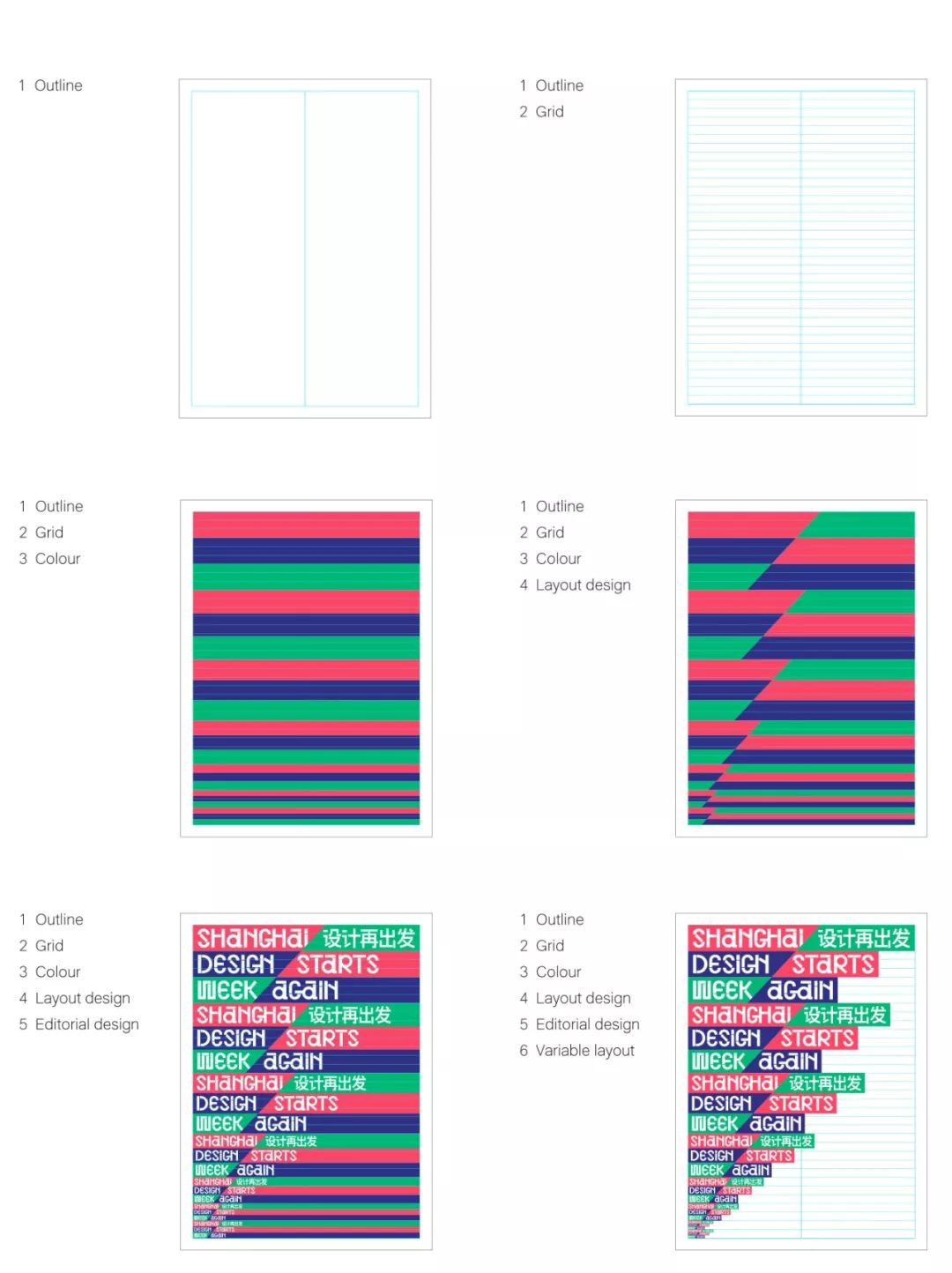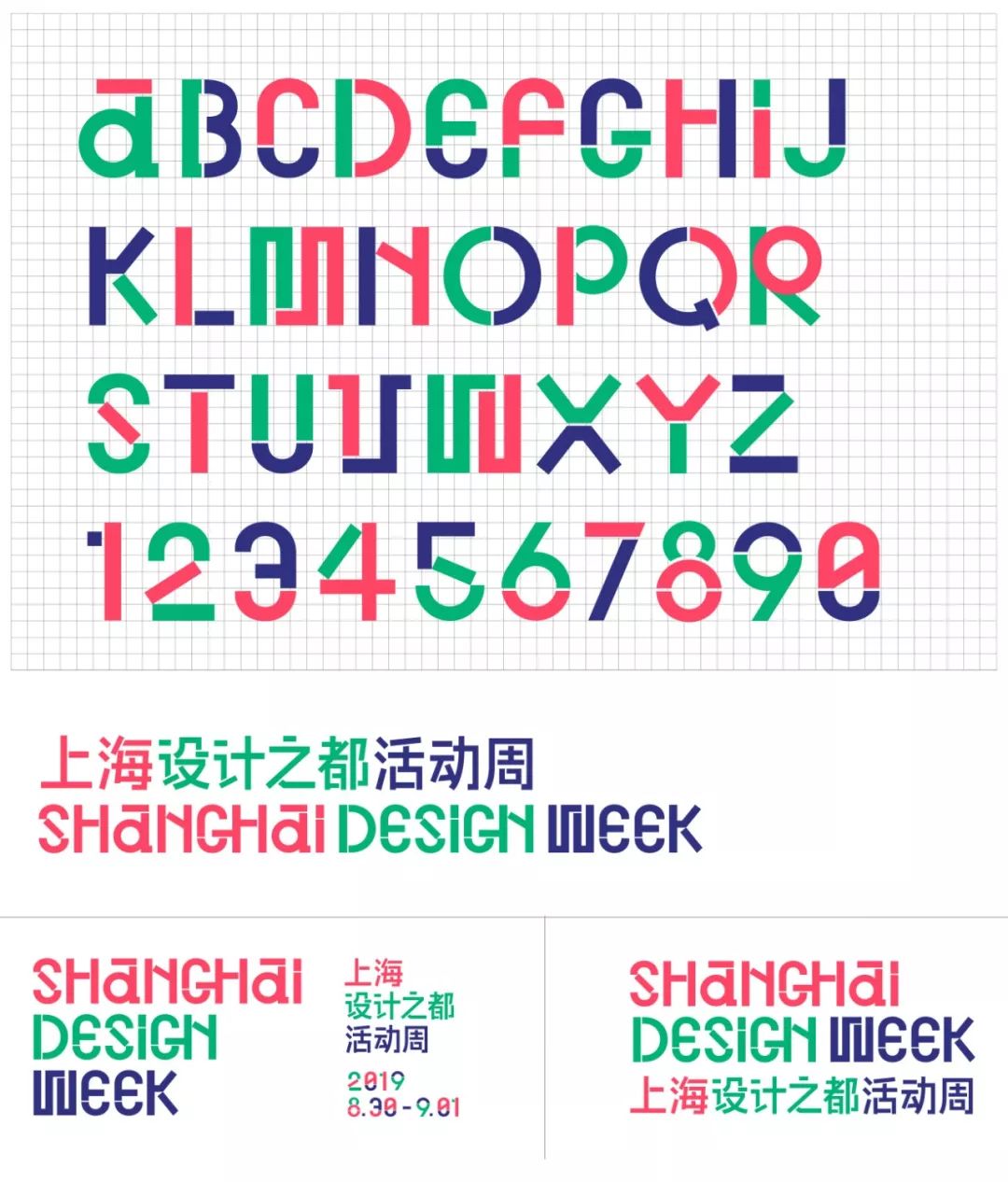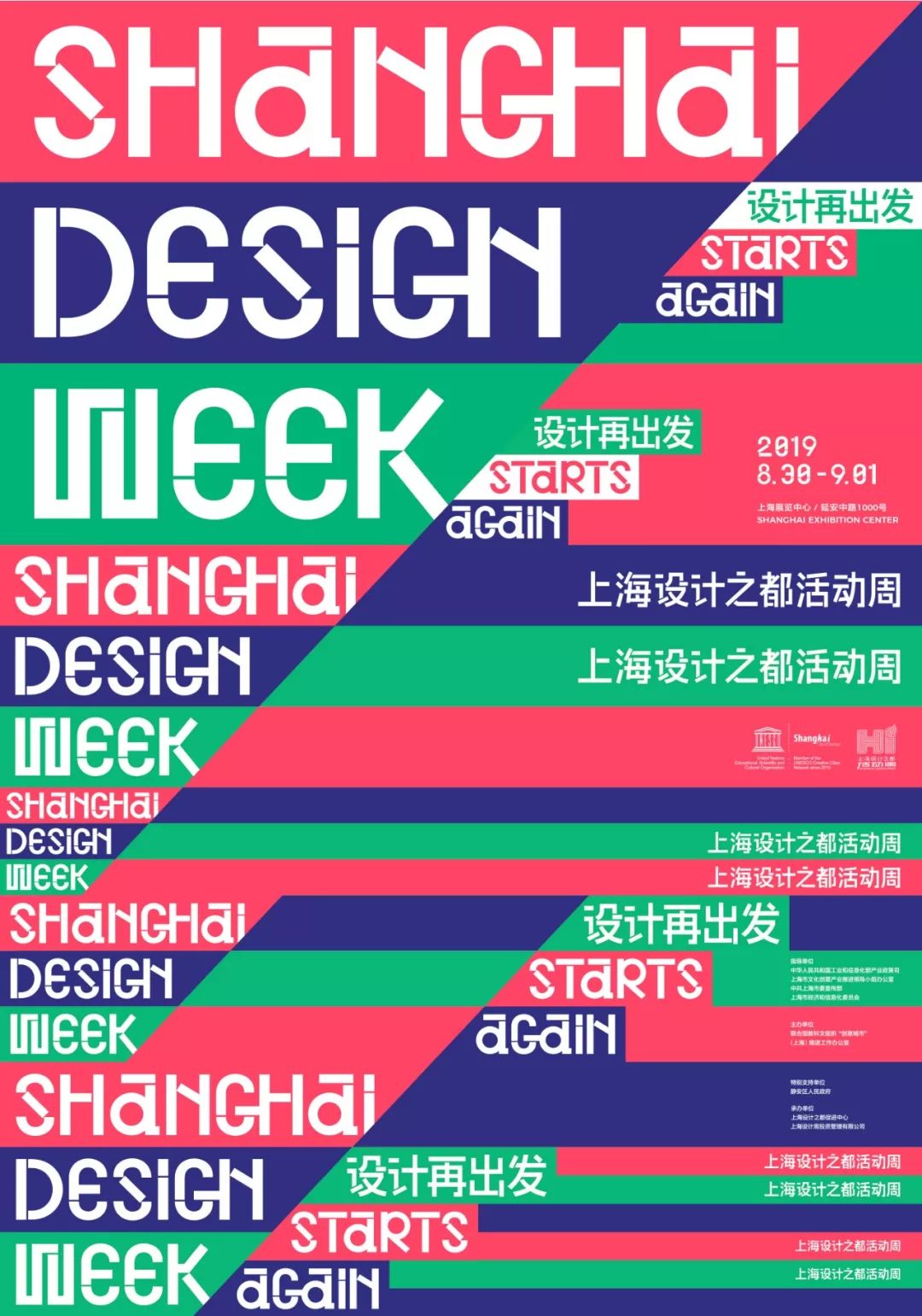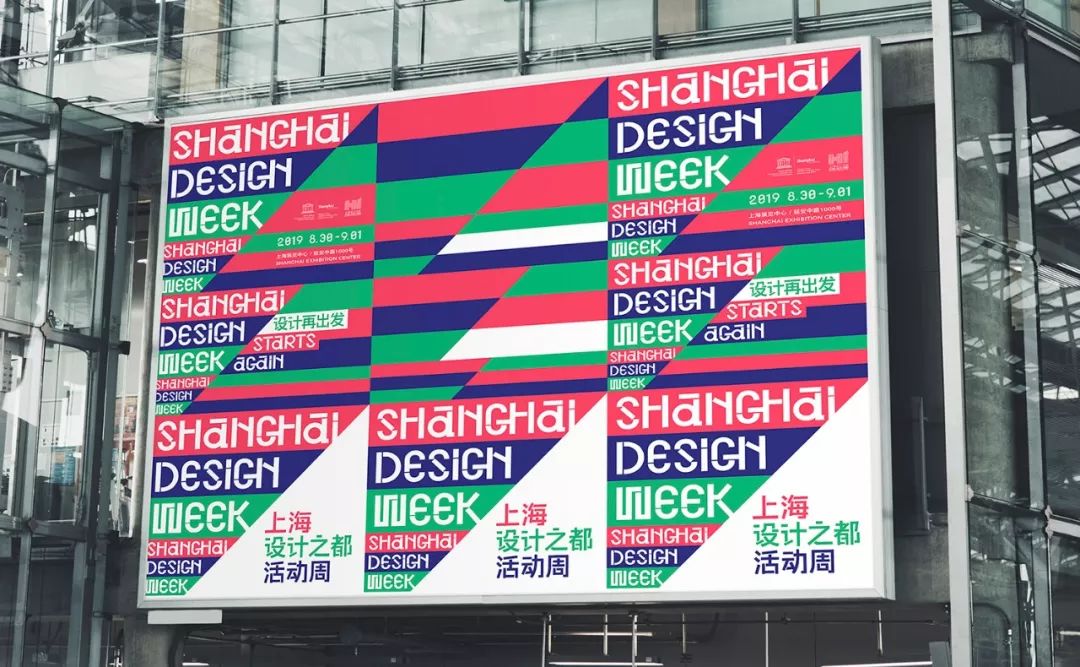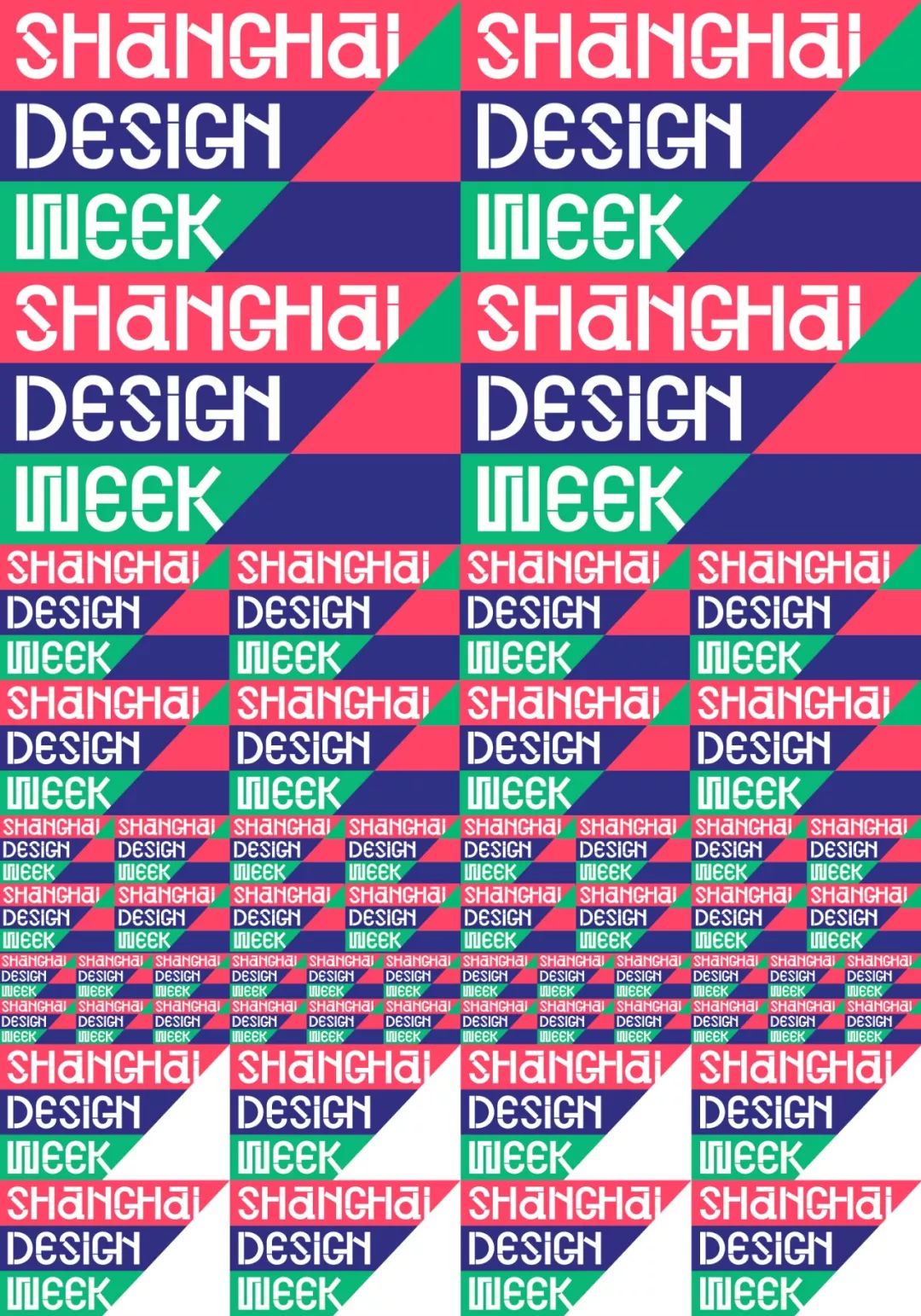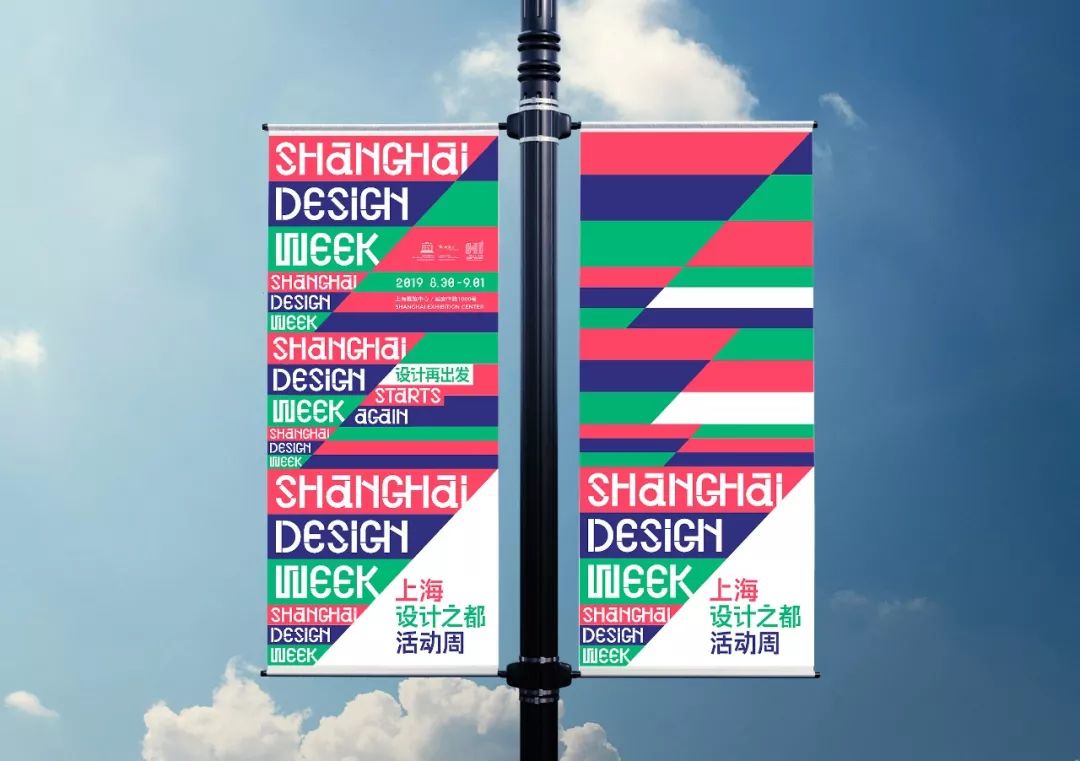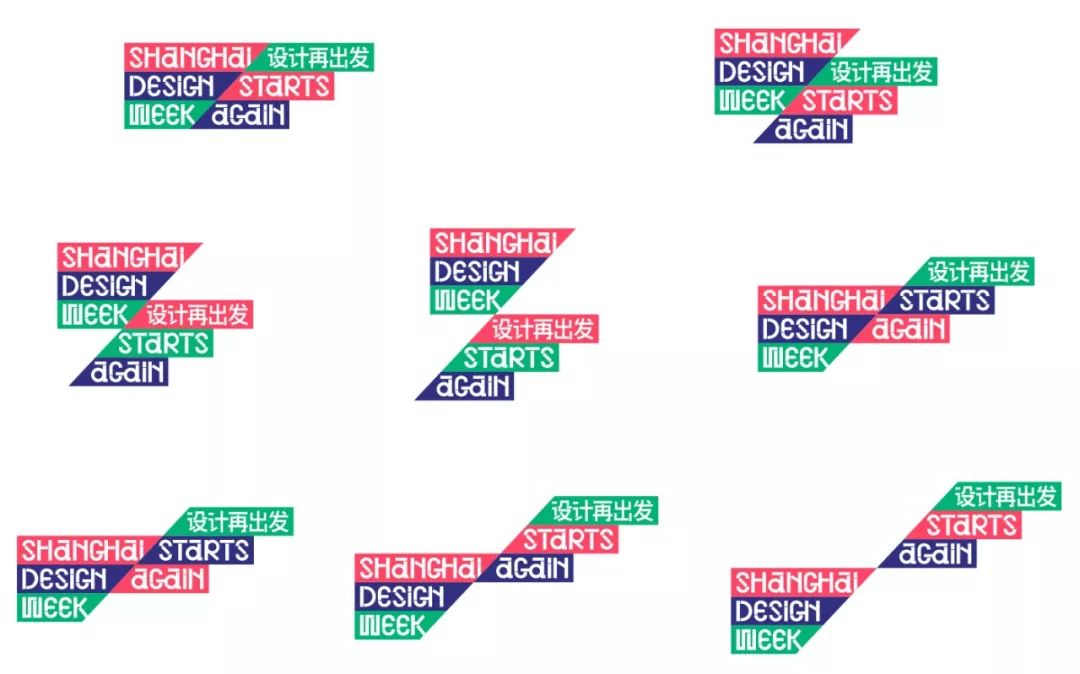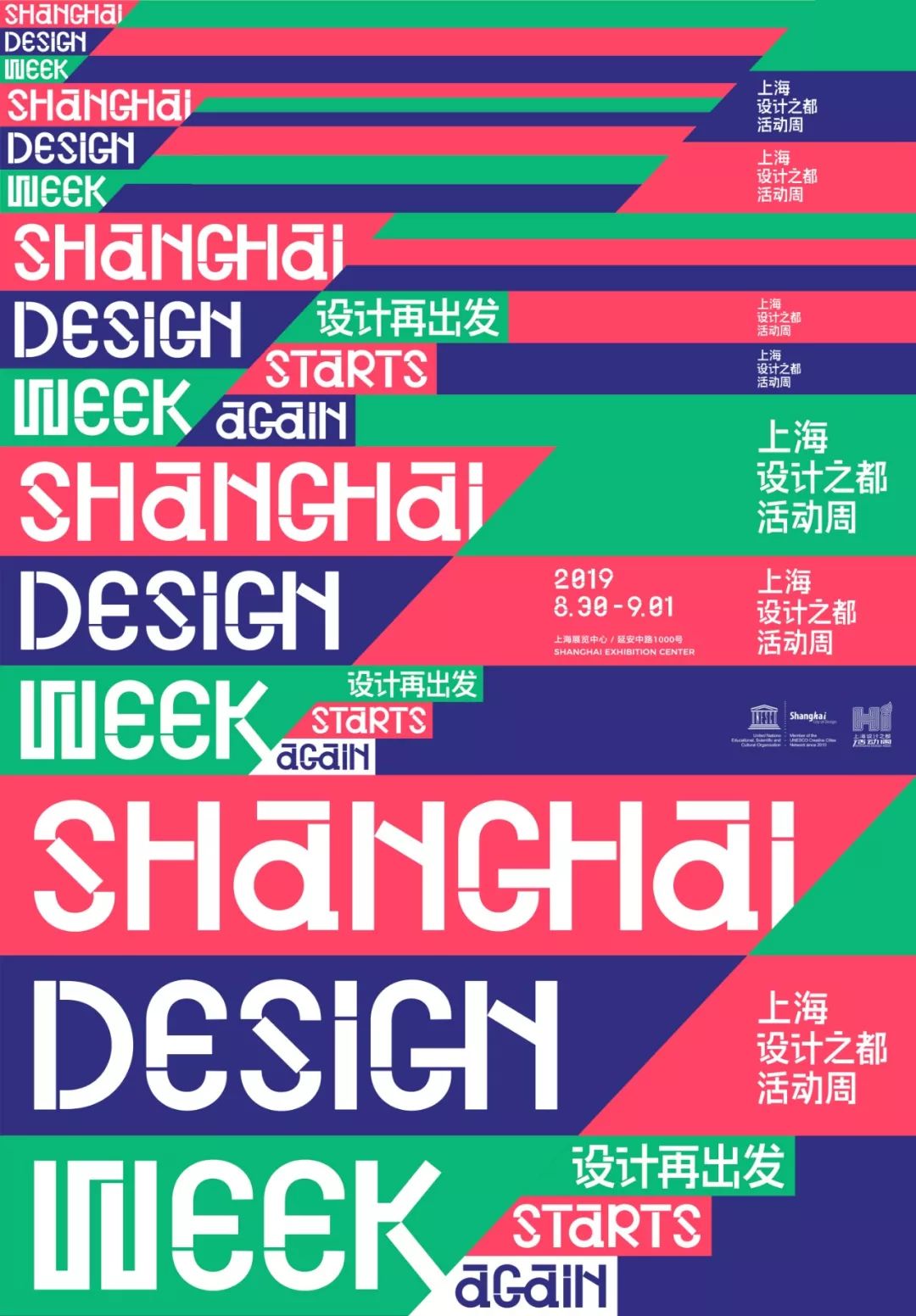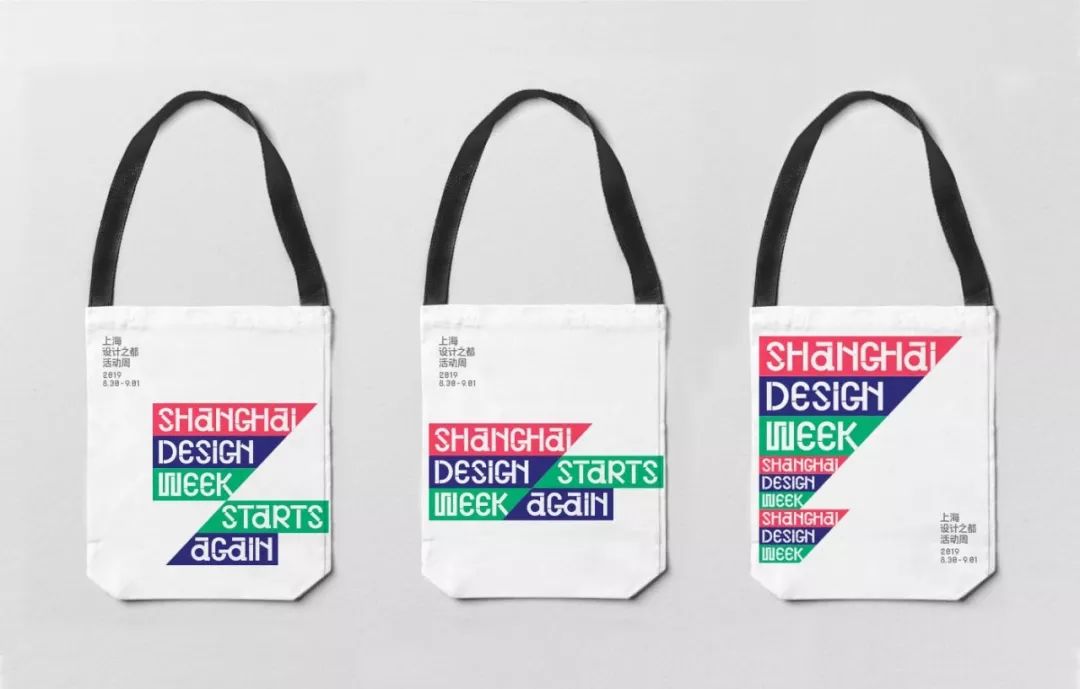
抢先看!2019上海设计周形象设计
城市的生活,就像一张网,固定着我们每一天的式样,在日复一日的倦怠中,编织着习惯的日常,却依然无法忽视,内心绵延不绝的渴望。于是,我放下机械的繁忙,清零过往,以涅槃之姿重启、再出发,尝试创造并改变着想象中的远方用一个全新的亮相,不负你望。
——  上海设计周
2019. 6
“创新设计发布平台”从“改变”开始
2019年,上海设计周的第八年,
或许,它更应该称为设计周重整出发的元年。
7年积淀,今天,是蜕变。
第八届的上海设计周将“设计再出发”作为这一季的主题,
新理念、新产品、新应用和新模式......
再创建、再启动、再延续、再循环......
新起点、新开始......
我们将以全新的视觉设计面貌,
描绘一个彰显城市特色和国际影响力的设计盛会。
我们的色彩 COLOUR
红色,是热情,是摩登,设计的出现让这个城市变得活色生香;
绿色,是生命,是延续,健康的生态让城市在自由呼吸中肆意徜徉;
蓝色,是信息,是未来,科技的设计力让诸多昔日的不可能变成当今的常态。
我们的字体  TYPOGRAPHY
绿色+蓝色?红色+绿色?
26个拼色的英文字母变换多彩,
动态的字体如同俏皮跳动着的音符,
诠释着城市生活的节奏感和律动感。
不同主题色的组合,讲述着设计与时尚的碰撞,
设计与生态的平衡,设计与科技的对话。
这是一款为“上海设计周”专属设计的图形字体。字体设计灵感:城市、结构、空间、艺术装饰(Art Deco)
我们的标志  LOGOTYPE
2019上海设计周Logo是多形态和动态表现形式。
设计师虞惠卿:全新的视觉设计让色块可自由改变结构、颜色和组合,以整体视觉元素为模块的生成设计,通过Processing编写程序,让任何人都可以调节按钮再设计,生成你心目中的完美比例和搭配。只要你有一颗蠢蠢欲动的设计之心,即便你是设计“小白”也能通过简单的参数调整,亲手参与创造出2019上海设计周VI画面。点击鼠标,左滑右滑,专属视觉设计技能GET!         2019上海设计周的色彩,你说了算!
应用设计 APPLICATION
设计师虞惠卿:上海设计周视觉系统在应用中,以网格化规范应用设计。预制活动中未知的图文信息量,通过网格布局优化信息传达,如:组织框架信息、参展商信息、论坛信息、合作方信息等等,在虚拟空间布局框架下,自由调整栅格比例和分栏,在一个规范的视觉系统下有序、合理地图文设计编排。
- 海报 POSTER:
- 招旗 BANNER:
衍生产品 DERIVATES AND PRODUCTS
导示系统 SIGNAGE SYSTEM
再出发的我们走出细分行业领域的设计界限,
将“大设计”的理念进行到底,
以开放包容的姿态接受
任何领域、任何形式的创新设计,
设计的主体当是“全民”,
设计带来的幸福感
理应弥漫于城市生活的各个角落。